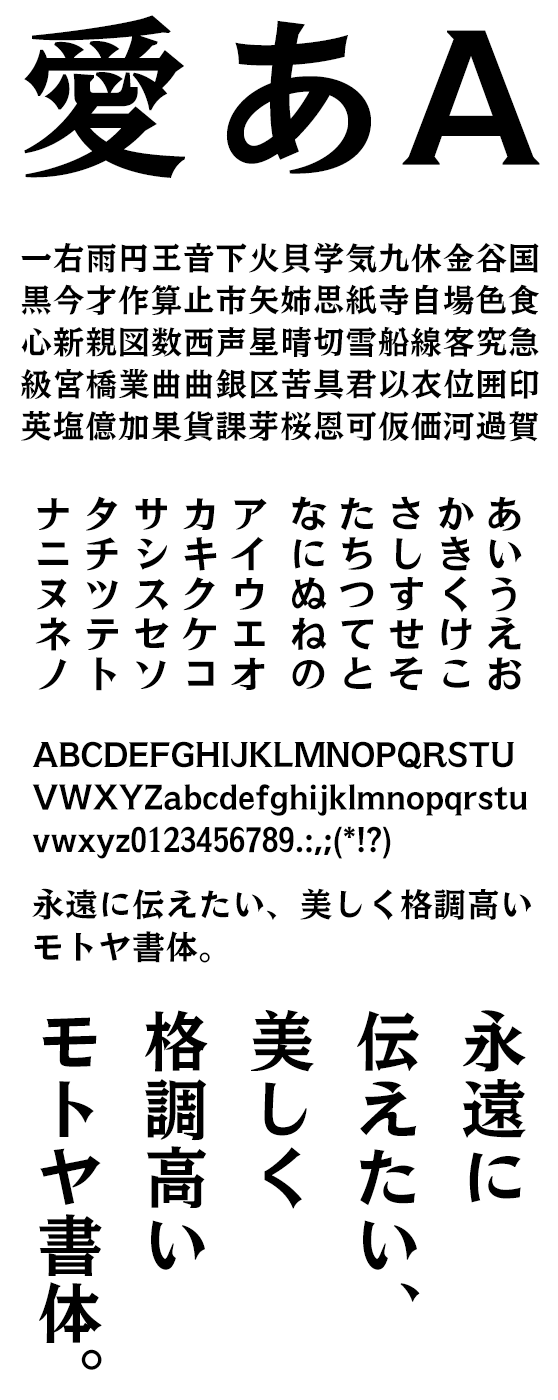
モトヤホンコン5 LiteN
MotoyaHongkongLiteN-W5
明朝体のようなデザインと、ゴシック体を思わせる力強さを併せ持った書体です。勢いのある文字 が特徴的なこの書体は、中国・香港で着想を得たことから「ホンコン」と命名され、1972 年に活字書体として販売しました。今回、活字時代の雰囲気はそのままに、デザインをさらに洗練させ、デジタルフォントとして帰って来ました。